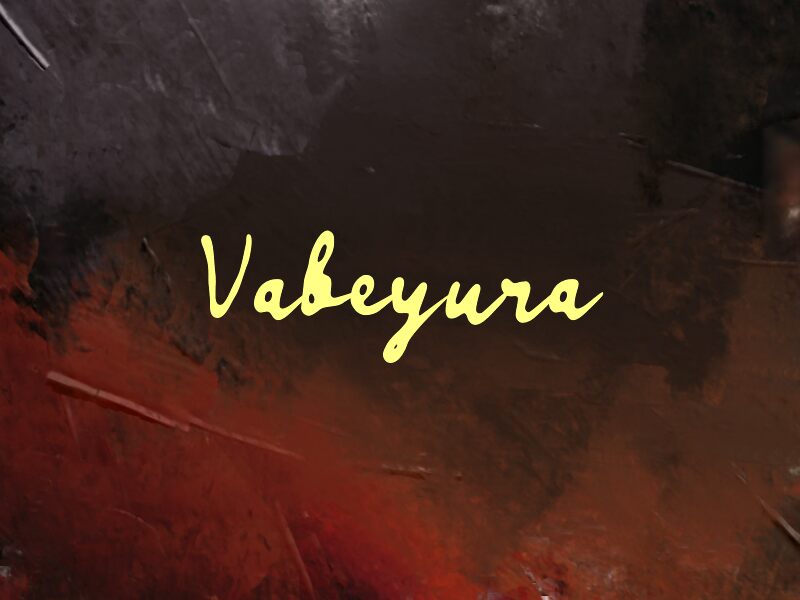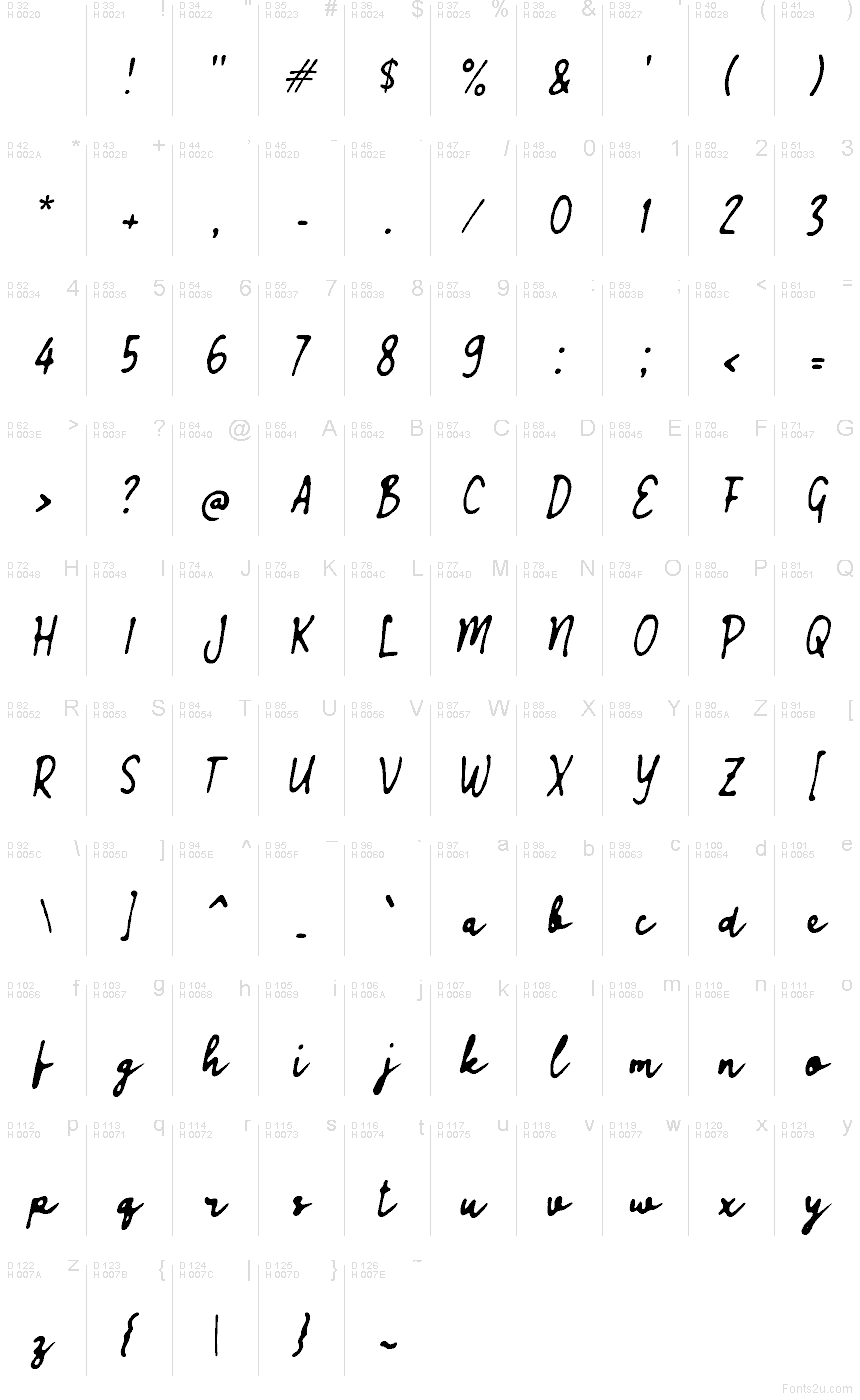
Vabeyura
Vabeyura od Wep je bezplatné ručně psané písmo s rychlým, rozmáchlým rytmem, díky němuž působí písmena spíše jako improvizovaný záznam než pečlivě vykreslený návrh. Tah zůstává tmavý a zaoblený, zatímco dlouhé horní a dolní dotahy dodávají písmu volný pohyb, připomínající podpis.
Tato energie se skvěle hodí pro loga produktů, grafiku na sociální sítě, etikety, plakáty k akcím nebo citátové karty, kde je osobitost důležitější než formální dokonalost. Krátké nadpisy a branding založený na názvech z něj těží nejvíce, protože protažené tahy a neformální spoje dodávají textu sebevědomý, ručně psaný vzhled.